三极拉钩体是一款可爱的创意字体,该字体起笔、收尾带钩,有很强的装饰性,富有强烈的节奏感。寓意拉钩上吊, 一百年不许变。
汉标追途体轻松活泼的笔画,俏皮可爱的构字,特别是一些转折处,采用笔画翘角的处理,配以俏皮的构字,将字体可爱的一面表现的淋漓尽致。
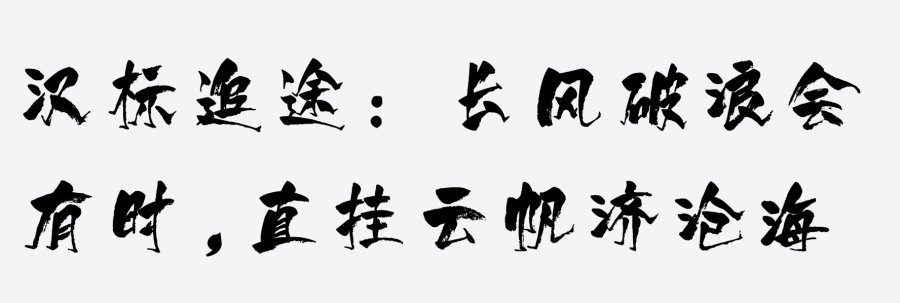
三极力量酷黑字体结构方正、精致。其字形稳健,个性简静秀美。适用于时尚类品牌的广告和产品包装设计。